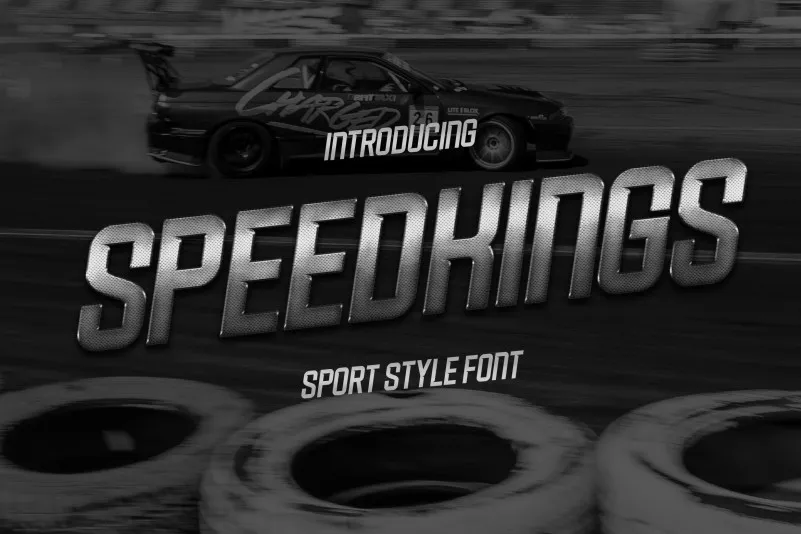
A fonte Speedkings Display é uma escolha ideal para aqueles buscando um estilo moderno e minimalista. Criada pelo Type Factory, esta fonte sans-serif oferece um visual único e atraente, perfeitamente projetado para uso em ambientes de marca ou logomarca. Seu design cuidadosamente refinado se adequa perfeitamente aos projetos que exigem uma presença moderna, como a criação de logotipos, títulos de capa, e até mesmo à montagem de revistas. Ideal tanto para uso em aplicações digitais quanto impressas, Speedkings Display é perfeito para quem busca criar um design contemporâneo que transmita clareza e simplicidade. Suas linhas leves e sua paleta de cores neutra fazem com que seja uma escolha ideal para a criação de e-sports, lifestyle e qualquer outro tipo de projetos em que deseja destacar seu estilo único.